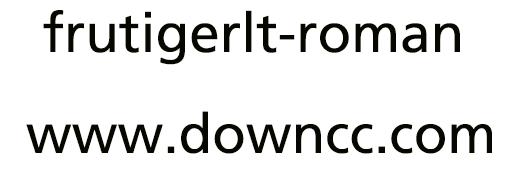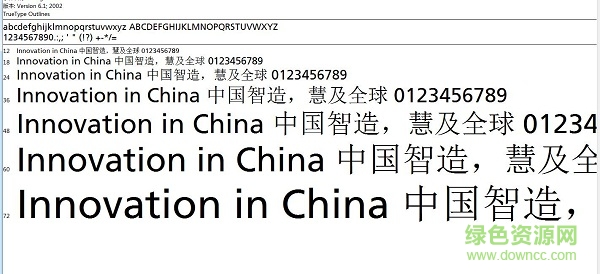
frutigerlt-roman字體
frutigerlt-roman字體是一款免費(fèi)的常規(guī)無(wú)襯線字體,字形干凈清晰度高,支持基本拉丁文、常見標(biāo)點(diǎn)符號(hào)、數(shù)學(xué)運(yùn)算符號(hào)的輸入,適合用在各種專業(yè)系統(tǒng)上,有需要者快來(lái)下載吧!
frutigerlt-roman